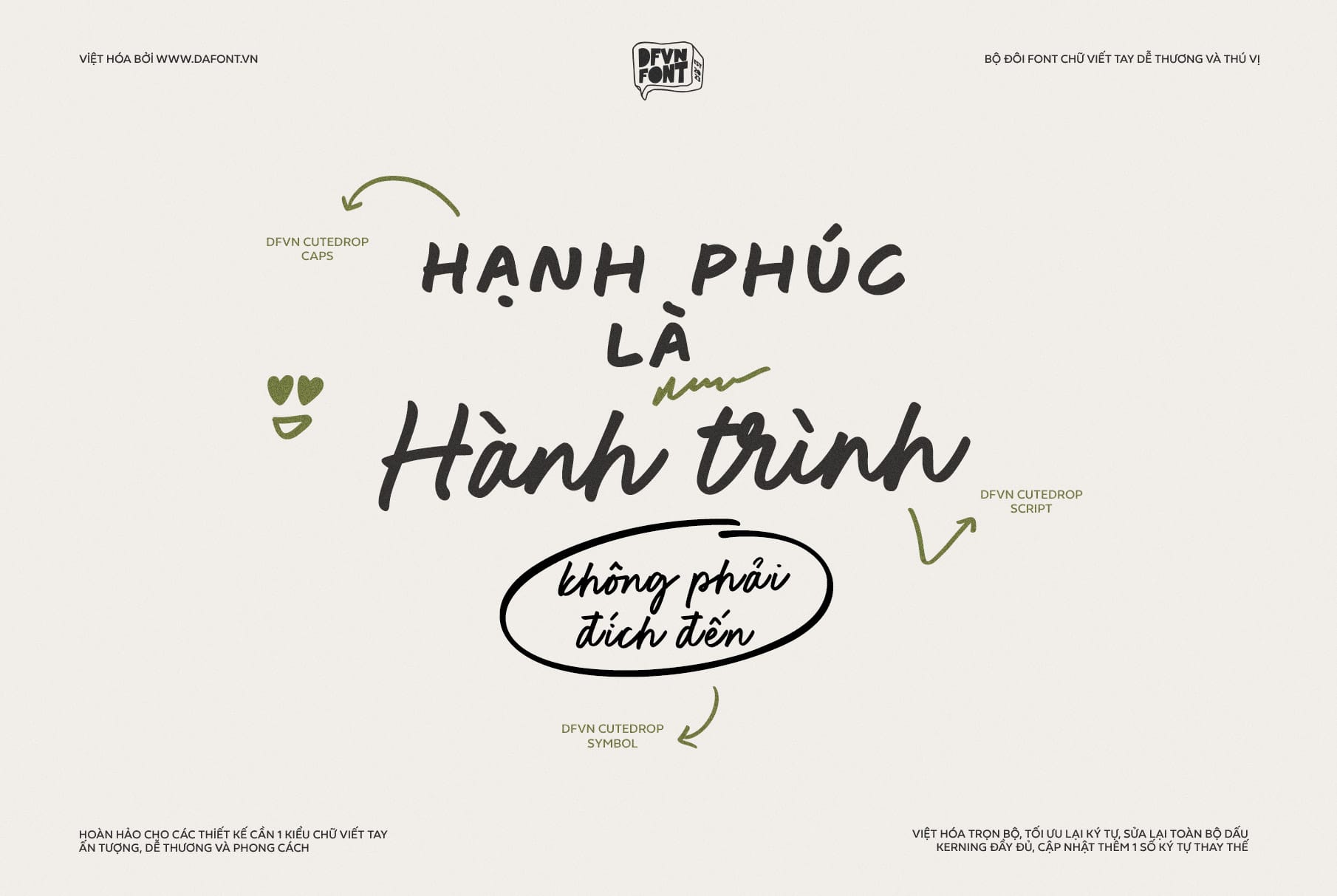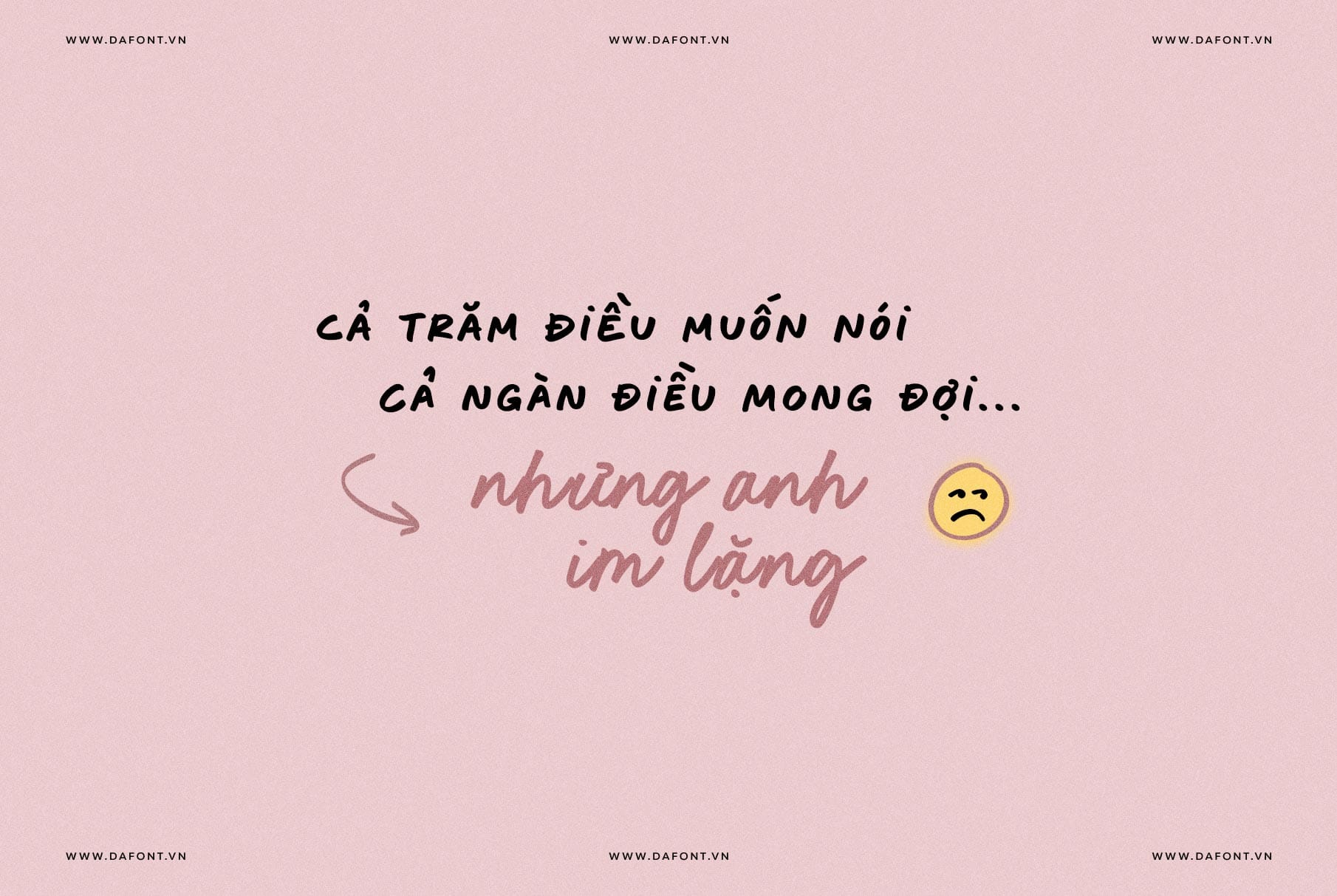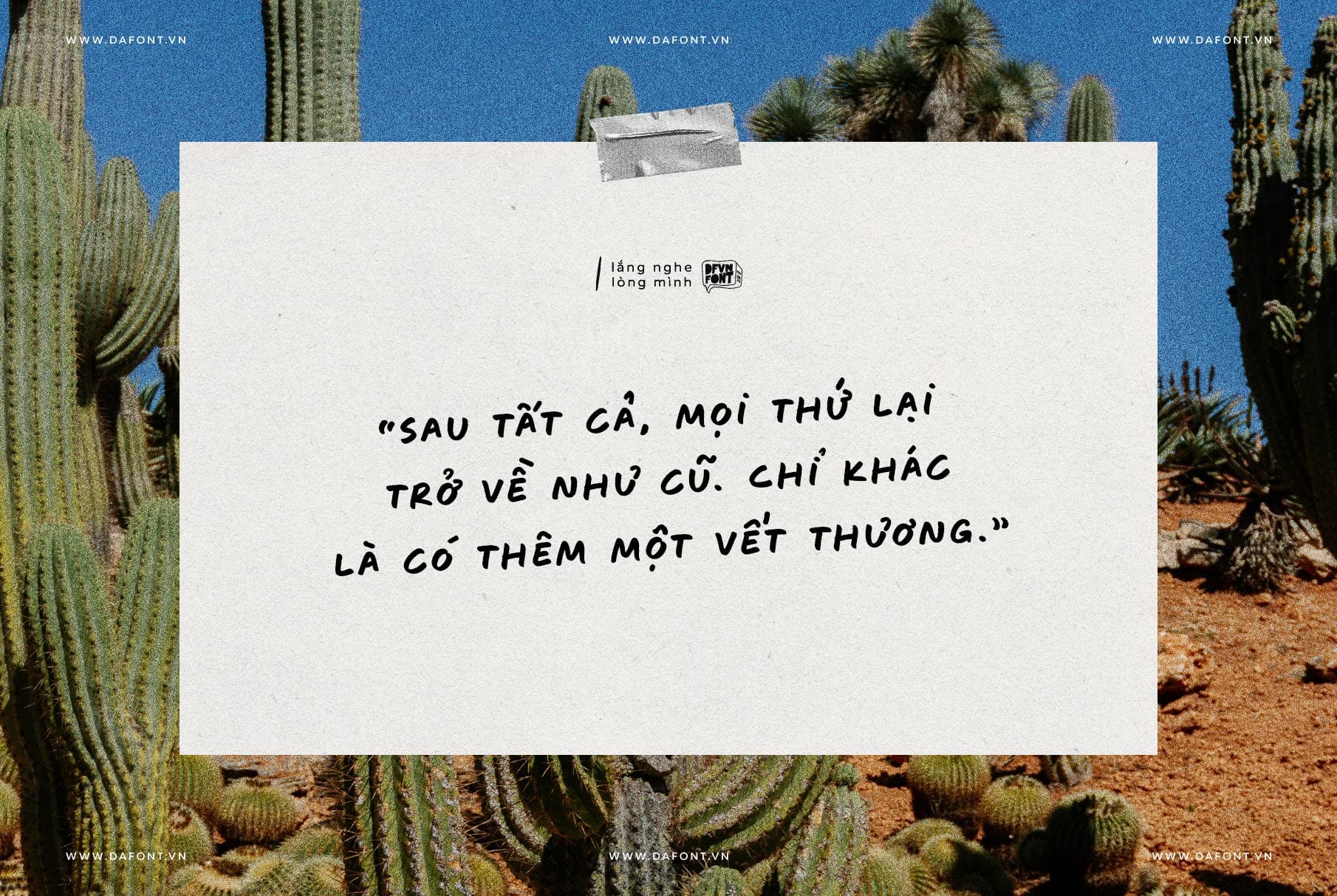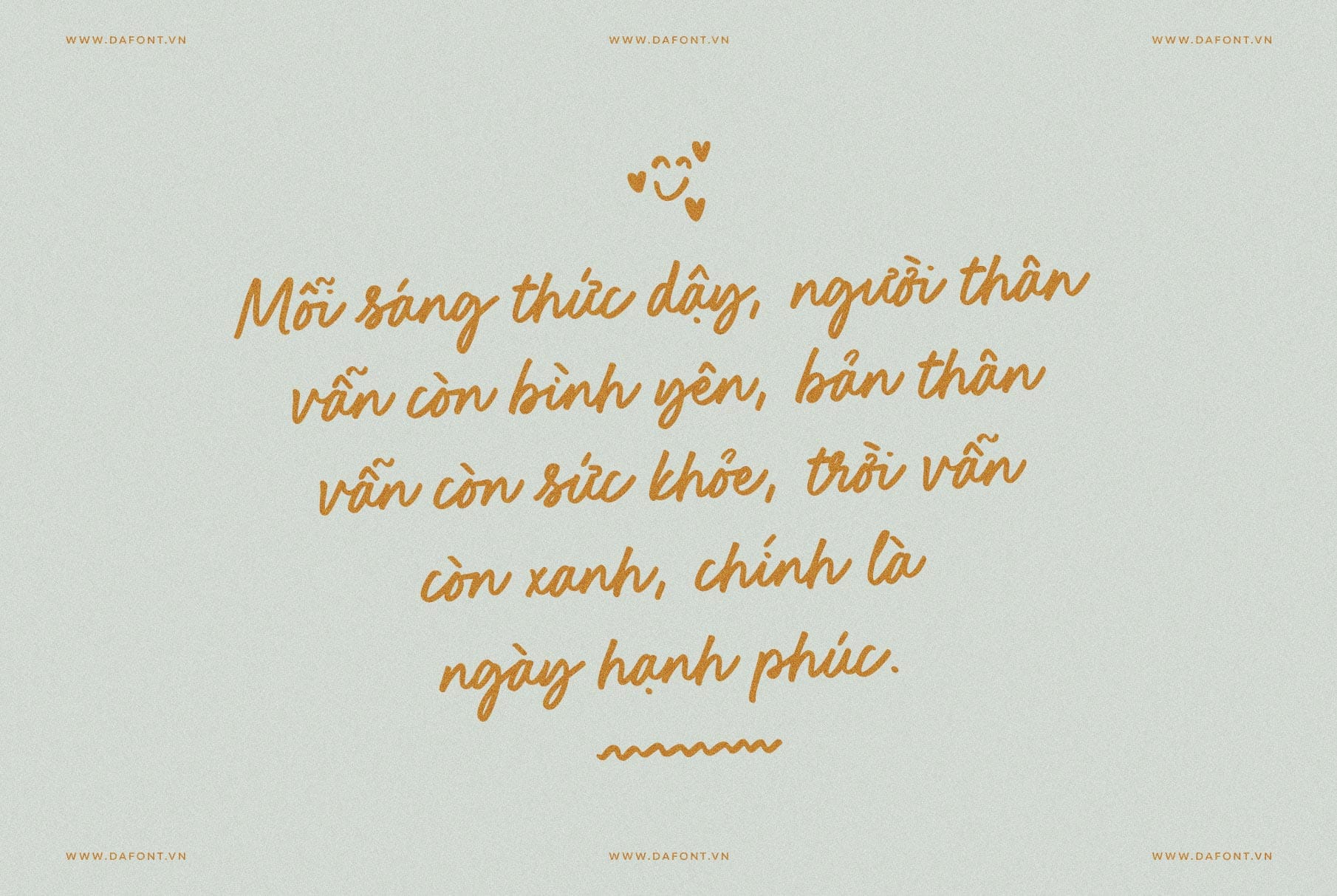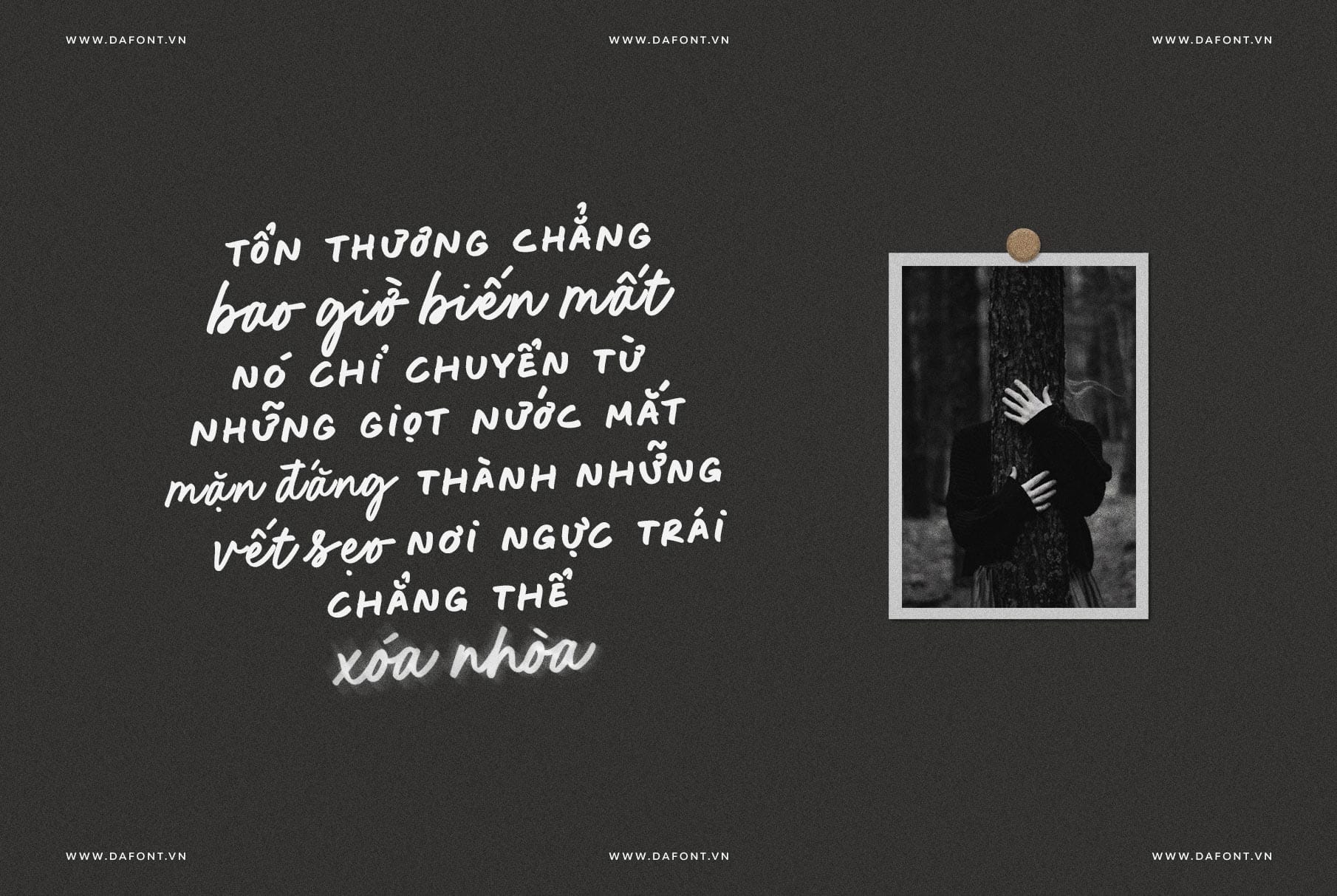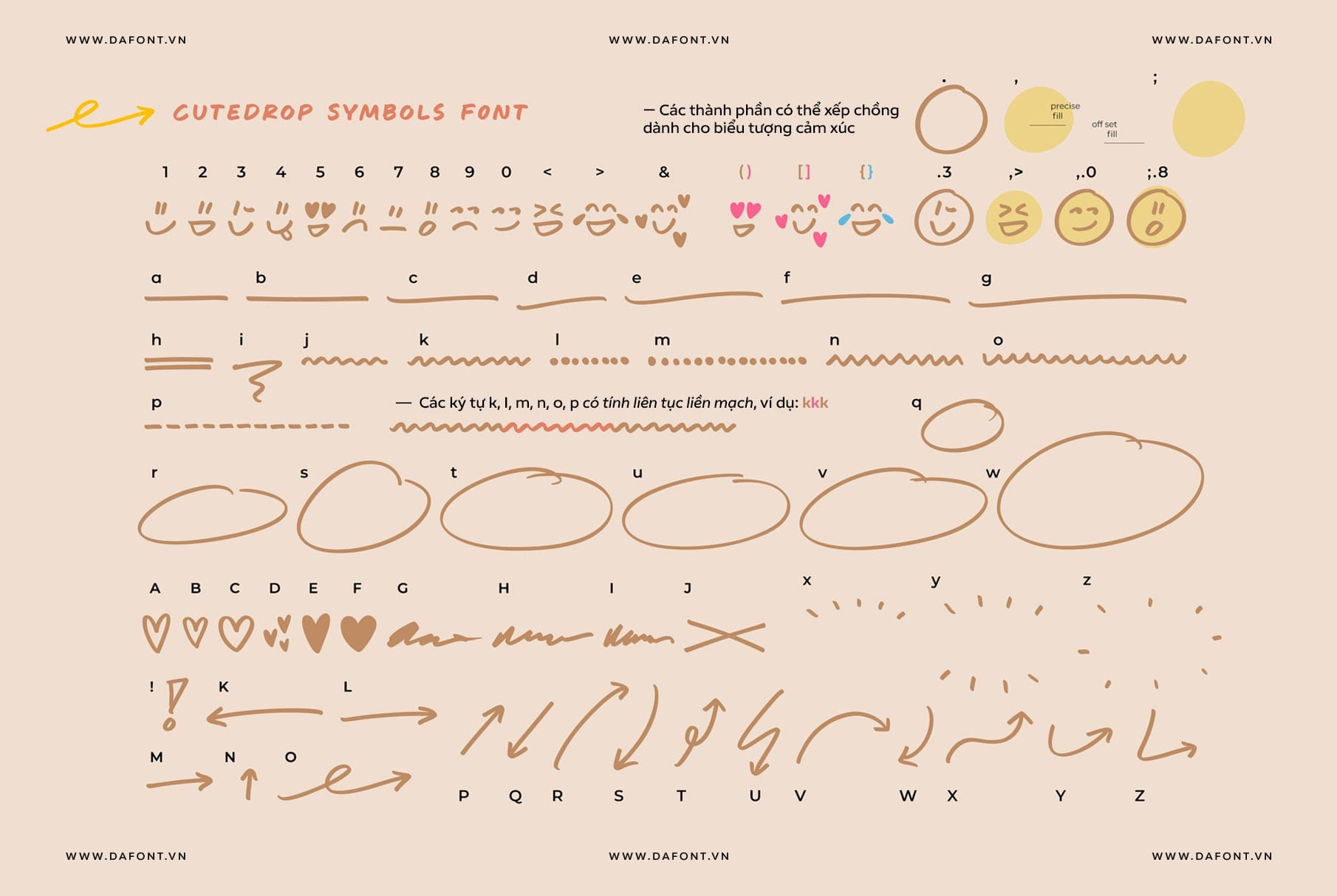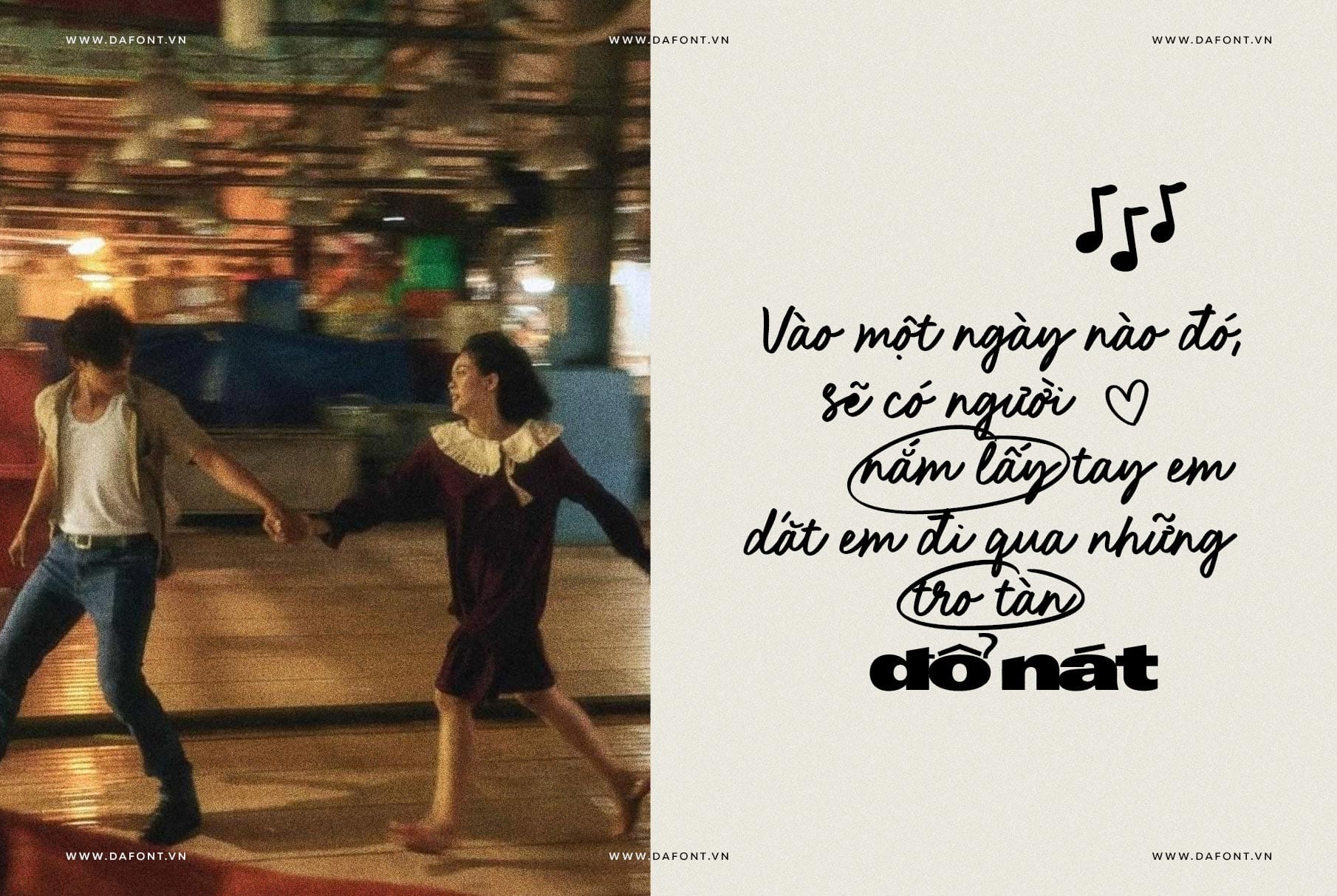
DFVN CuteDrop là một bộ đôi font chữ viết tay (handwritten font duo) đầy cuốn hút. Bộ font này bao gồm 2 phông chữ chính: một font chữ script với các nét chữ liên kết mượt mà và một font chữ all-caps với các chữ in hoa mạnh mẽ. Cả hai đều được vẽ tay bằng cùng một bút marker, đảm bảo sự đồng nhất và hài hòa trong thiết kế.
Điểm đặc biệt của CuteDrop là bộ biểu tượng (symbols) vẽ tay đi kèm, bao gồm 65 yếu tố như emoji, trái tim, đường gạch chân, mũi tên, vòng tròn, và các nét vẽ nguệch ngoạc, giúp tăng thêm sự đáng yêu và linh hoạt cho các dự án thiết kế.
Đặc điểm nổi bật DFVN CuteDrop
DFVN CuteDrop mang phong cách viết tay vui tươi, thoải mái, với các nét chữ mềm mại và tự nhiên, tạo cảm giác như được viết tay thật sự. Font chữ script có các ký tự liên kết, mang lại vẻ ngoài chân thực và gần gũi, rất phù hợp cho các thiết kế cần sự cá nhân hóa. Trong khi đó, font chữ all-caps bổ sung sự mạnh mẽ và nổi bật, lý tưởng cho tiêu đề hoặc các điểm nhấn trong thiết kế.
Bộ biểu tượng CuteDrop Symbols là một điểm nhấn độc đáo, với 65 yếu tố được vẽ tay bằng cùng bút marker, đảm bảo sự đồng nhất với 2 font chữ chính. Các yếu tố này bao gồm emoji, trái tim, mũi tên, vòng tròn, và các nét vẽ tùy ý, giúp nhà thiết kế dễ dàng thêm các chi tiết trang trí mà không cần sử dụng tài liệu đồ họa bổ sung.
Bộ font chữ DFVN CuteDrop Việt hóa bao gồm 3 font chữ:
- DFVN CuteDrop Script – một font viết tay đẹp mắt bao gồm một tập hợp các chữ cái hoa, chữ cái thường và một loạt các ký tự thay thế được thêm vào.
- DFVN CuteDrop Caps – một font chữ với 2 bộ chữ in hoa được thiết kế in hoa toàn bộ
- DFVN CuteDrop Symbols – một font chữ dingbats gồm 65 thành phần được vẽ tay
Ứng dụng của CuteDrop trong thiết kế
CuteDrop là một bộ font đa năng, phù hợp cho nhiều loại dự án thiết kế cần sự vui tươi, cá tính, và phong cách thủ công. Dưới đây là một số ứng dụng phổ biến:
- Poster và Flyer: Tạo các thiết kế quảng cáo bắt mắt với tiêu đề in hoa từ CuteDrop Caps và nội dung mềm mại từ CuteDrop Script.
- Mạng xã hội: Thiết kế hình ảnh cho Instagram, Tiktok hoặc Facebook với phong cách viết tay gần gũi, kết hợp các biểu tượng như trái tim hoặc emoji.
- Logo và Thương hiệu: Sử dụng CuteDrop để tạo logo hoặc các yếu tố thương hiệu độc đáo, mang lại cảm giác thân thiện và sáng tạo.
- Thiệp mời và Thiệp chúc mừng: Thêm nét cá nhân vào các thiết kế thiệp cưới, sinh nhật, hoặc sự kiện đặc biệt.
- Bao bì sản phẩm: Làm đẹp bao bì cho các sản phẩm như đồ ăn, mỹ phẩm, hoặc đồ chơi trẻ em với typography vui tươi.
Font này có thể được sử dụng trong cả thiết kế kỹ thuật số và in ấn, từ các dự án cá nhân nhỏ đến các chiến dịch thương hiệu lớn. Sự linh hoạt của DFVN CuteDrop font Việt hóa giúp nó trở thành một tài sản quý giá cho các nhà thiết kế ở mọi cấp độ.
DFVN CuteDrop – Font viết tay đẹp mắt
CuteDrop là một bộ font chữ viết tay đáng yêu, linh hoạt, và đầy sáng tạo. Với sự kết hợp giữa font chữ script, all-caps, và bộ biểu tượng vẽ tay, CuteDrop mang lại sự đồng nhất và phong cách thủ công cho mọi dự án thiết kế. Dù bạn đang tạo poster, hình ảnh mạng xã hội, logo, hay bao bì sản phẩm, CuteDrop chắc chắn sẽ là một lựa chọn tuyệt vời để truyền tải cảm xúc và tạo nên sự khác biệt.
Bộ font DFVN CuteDrop được Việt hóa cẩn thận, với đầy đủ ký tự và dấu được tối ưu tinh tế. Các dấu tiếng Việt được sắp đặt ngẫu hứng một cách nghệ thuật, tái hiện chân thực nét bút tay tự nhiên. Bên cạnh đó, toàn bộ font đã được điều chỉnh kerning kỹ lưỡng và tích hợp đầy đủ các tính năng Opentype.